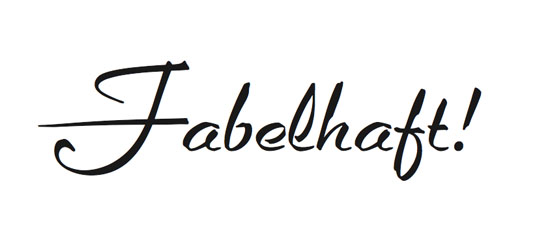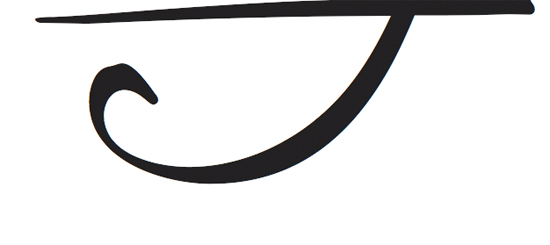
Die Form wiegt bestimmt zwei Pfund oder so.
Das sind in etwa a Kilo oder 100 Deka. Richtig? :D
Kilo... watt oder wat?
(zu mehr bin ich um diese Zeit noch nicht fähig)
Entschuldigung,
ganz vergessen, aber lautet nicht die oberste Typo-Quiz-Spielregel:
Wer eine Schrift erkennt, muss zwingend weitermachen, sonst wandert
er mit Blei an den Füßen in den nächsten See?
Also, passend zur Jahreszeit, etwas Leichtes, Sommerliches,
nicht Schweinshaxe mit Knödeln oder Guns N’ Roses (ich meine natürlich Gänsebraten un’ Rotkohl).
Die Bilder stammen aus der Offizin Schmorkohl – Qualität hat einen Namen – das »H« wurde auf einer Kinderpresse
gedruckt, »ambBrgS» wurde aufwendig gestempelt.
PS: »wenn ich sie angedruckt habe, schenke ich Dir die ausgebundene Satzform, wenn Du magst.«
Darüber würde ich mich ernsthaft sehr sehr freuen.
und ich dachte schon: Sommerloch – macht eh keiner mit.
Hiermit übergebe ich an den neuen Quizmaster und
PS: Ich halte mich raus, ich kenn eh nur die Holla und die auch nur flüchtig.
So, eine neue Runde (ich glaube leicht).
Übrigens: schön dass es hier weider Schmorkohl gibt.
Ähnlich wie beim Logo & Co.-Quizz für den Fachmann zu einfach :)
Das „m” ist aus der Berthold Formata Bold Condensed.
Jetzt suche ich mal was richtig schwieriges.
Ja mach mal. Ich hatte – außer sehr okulten Freefonts – grade nichts schwierigeres zur Hand.
Stimmt. Meine Lieblings-Garamond (neben der Amsterdam, die für mich fast genauso aussieht).
Schwungvoller geht's nicht.
Bitte weitermachen. :)
So, wie gewünscht, jetzt wird es so mittelscharf.
PS: Mein Typo-Quiz-Suchtberater
rät mir dringlichst zum kalten Entzug.
Mhh... Mhh...
Das F der Caprice (Martin Wilke) vielleicht ?!
Chapeau!
»Caprice« Martin Wilke, Berthold, 1939
Oha, da kommt gerade eine Gruppe weiß gekleideter Herrn ...
»Wie, Aussteigerprogramm für Typoquizverrückte?«
»Noch nie davon gehört?«
»Und was soll überhaupt diese seltsame Jacke?«
»ARGHHH!!!«
Okay, dann mach ich weiter:
Zuerst mal was einfaches, morgen vormittag suche ich dann noch eine
schwere Aufgabe heraus - versprochen! :)
Trau ich mich? Trau ich mich nicht? Ich trau mich - mehr als Spott und Hohn kann es nicht hageln, aber Ehre gilt es zu gewinnen ;-)
Trump Mediaeval?
Mein lieber M.W,
die Bembo ist es leider nicht. Die gesuchte Schönheit, allerorten vielleicht ein wenig unterschätzt, ist deutlich jünger (geschaffen in den Vierzigern des vorigen Jahrhunderts).